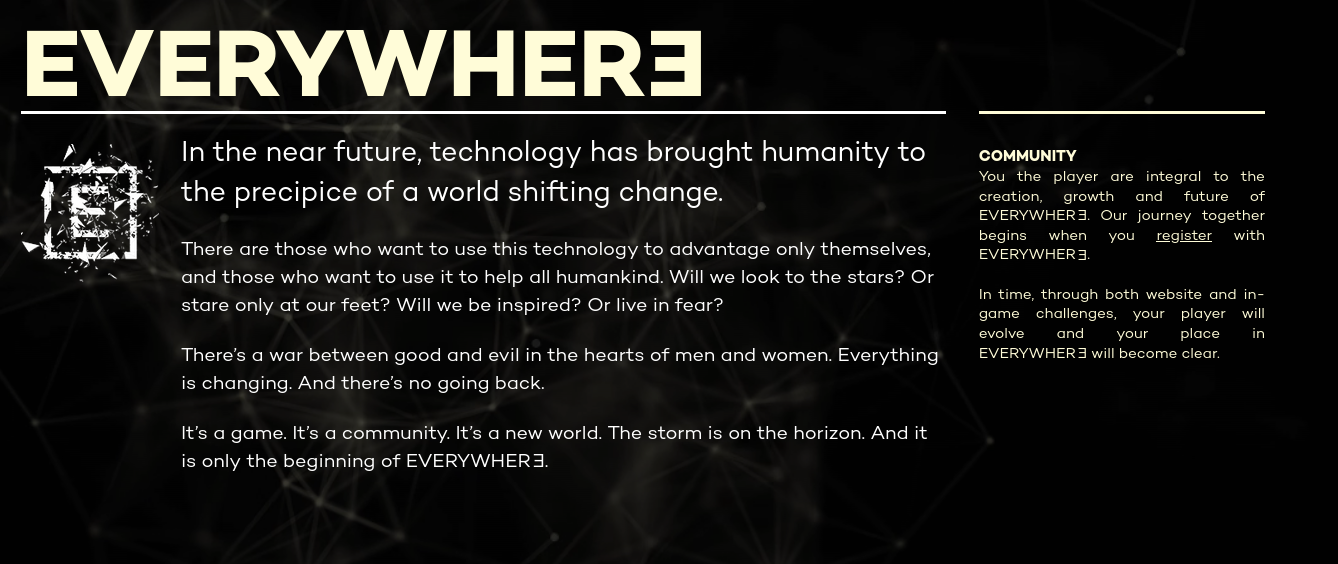
Name der Groteske auf Website von Build a Rocket Boy gesucht
ich würde gerne wissen, welche Schrift auf deren Website verwendet wird. Hier ein Screenshoot und der link. (Und ob jemand eine kostenfreie Schrift kennt, die dieser ähnlich genug ist, um sie in einer Bewerbung zu nutzen.)
Ein Frutiger-Klon? Dafür ist das R zu gestaucht …EverywherE.png.127b362225237514b12443c82fe178b6.png